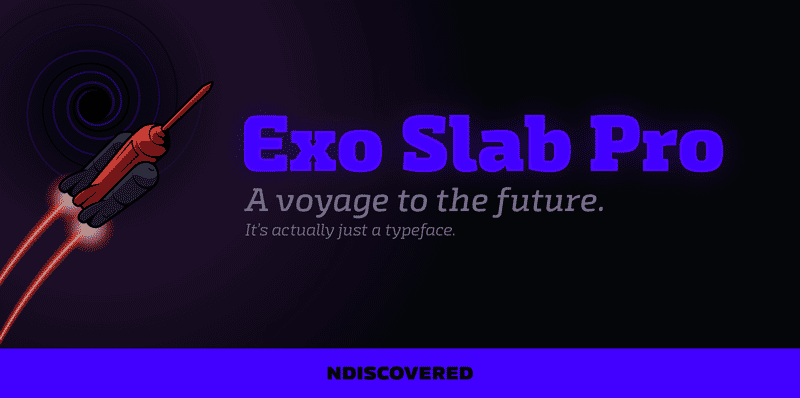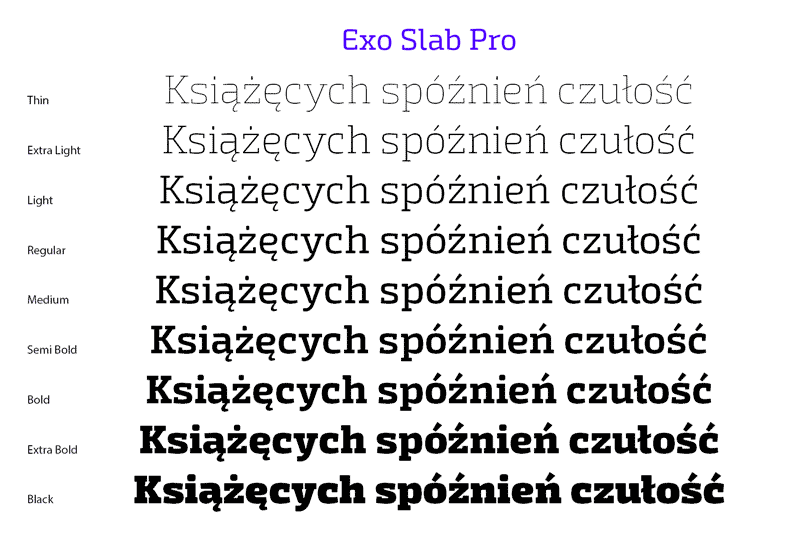
Font Exo Slab Pro
Nasze studio graficzne zakupiło nową rodzinę fontów z szeryfami blokowymi, Exo Slab Pro. Autorem jest Natanel Gama. Zestaw skład się z 9 odmian grubości wraz z italikami.
Font nadaje się doskonale do zastosowań w materiałach technicznych i identyfikacji wizualnej firm. Cena rodziny to 330$.